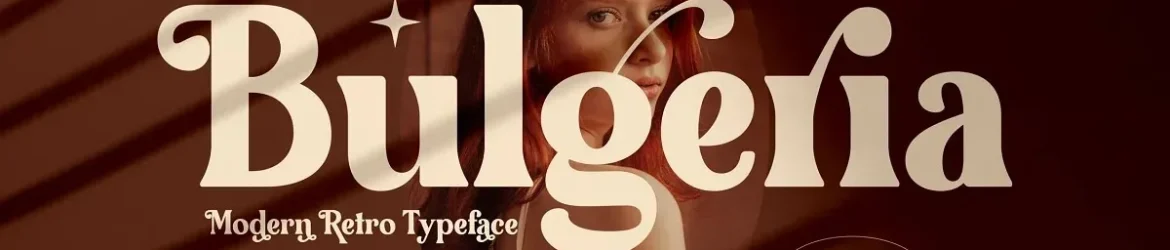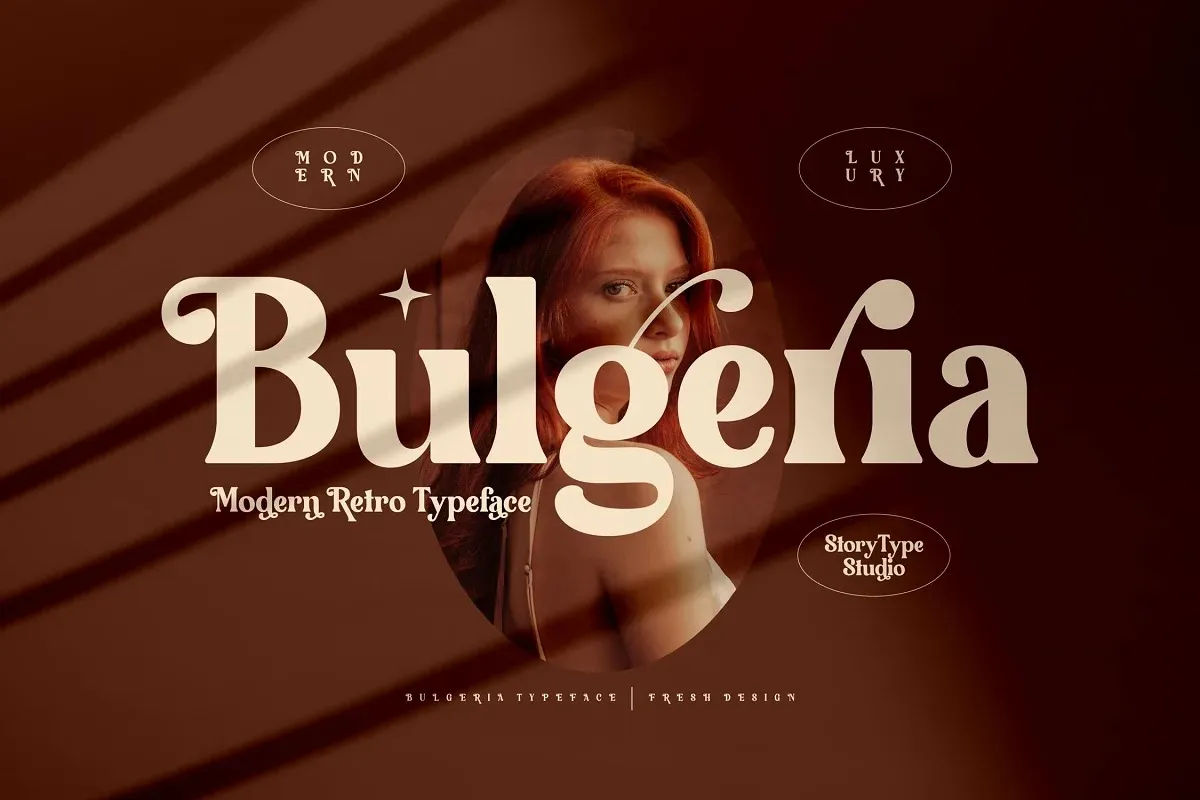
Bulgeria Font – Fonte Grátis
Bulgeria Font
A Bulgeria Font é uma elegante tipografia serif que traz arquitetura clássica misturada com uma aparente modernidade. Criada pela Storytype Studio, esta fonte possui formas perfeitas para aplicação em diversas áreas, como logotipos de luxo e sofisticação, títulos de livros ou filmes, marcas de roupas, letras digitais, citações e muito mais. A Bulgeria é ideal para qualquer projeto que desejávamos criar algo belamente sofisticado. Seja no design de um logotipo para uma marca fashionista ou em um título de filme elegante, a Bulgeria fará da sua criação algo memorable e impecável. Engane-se entre nossos projetos digitais e deixe-nos ajudar você a fazer com que o seu projeto brilhe ao encobrir cada detalhe do design.